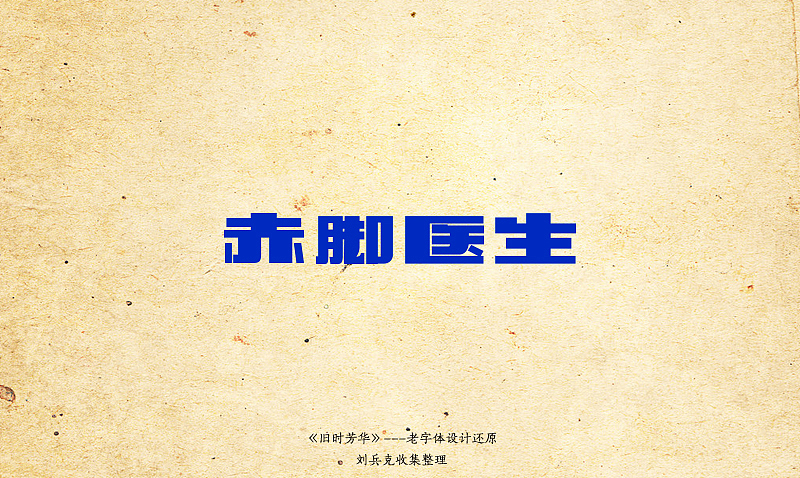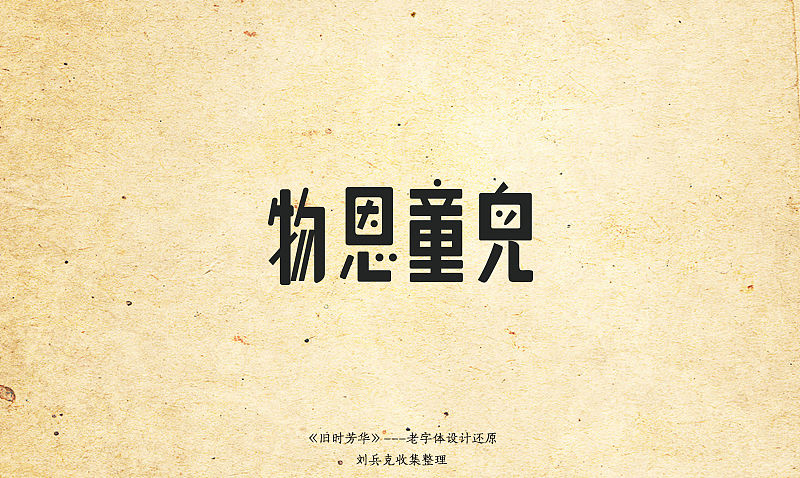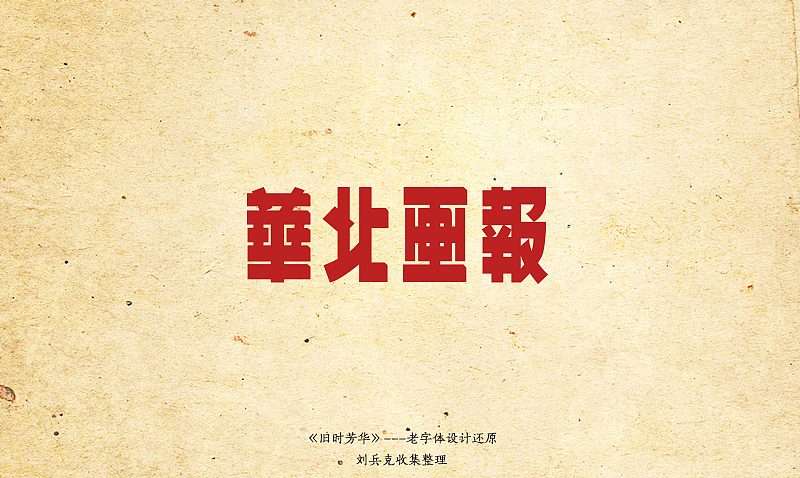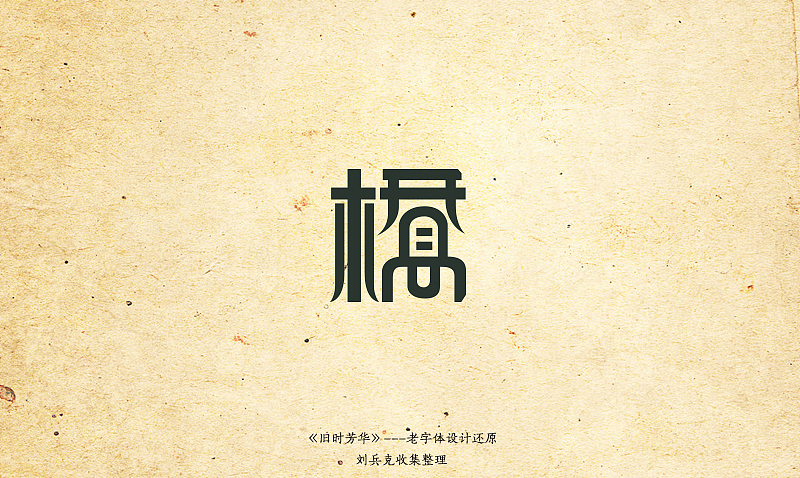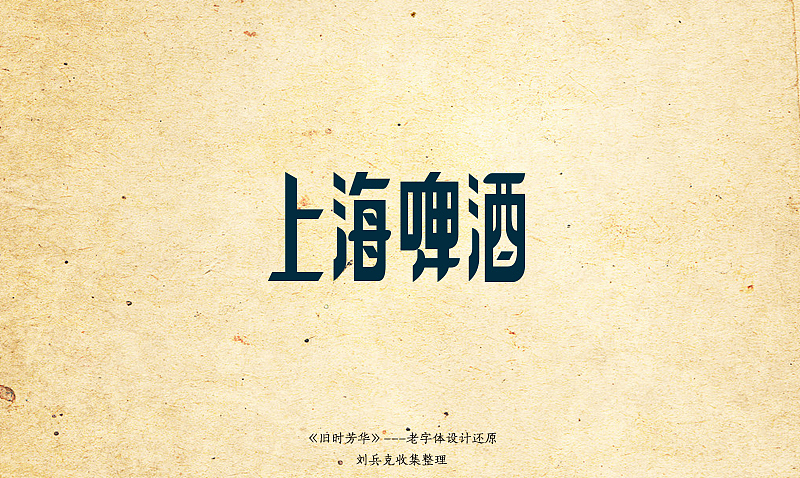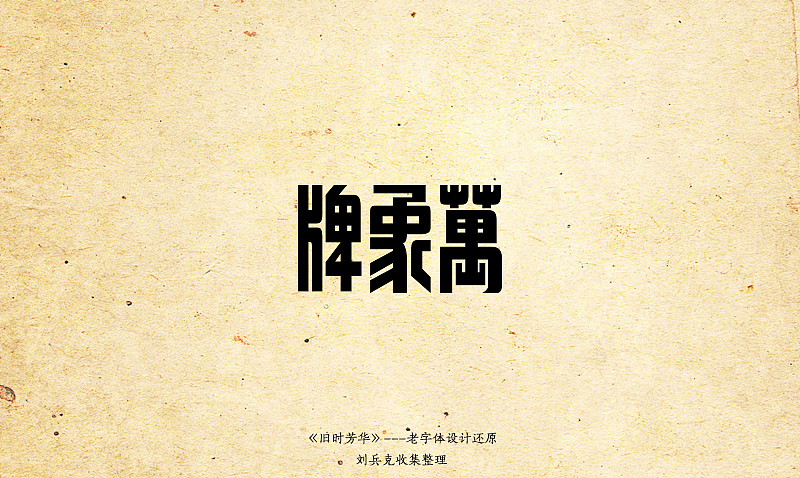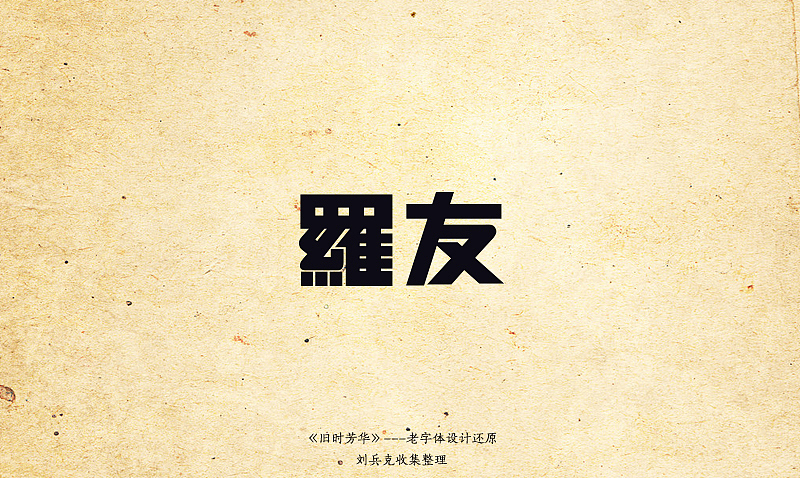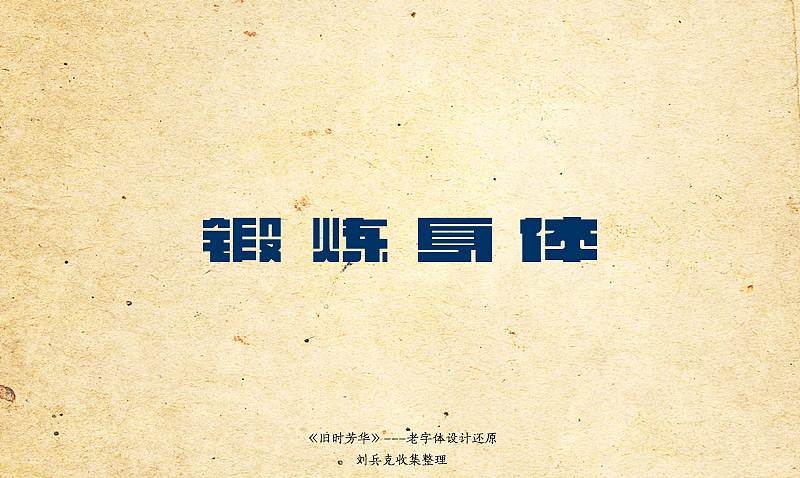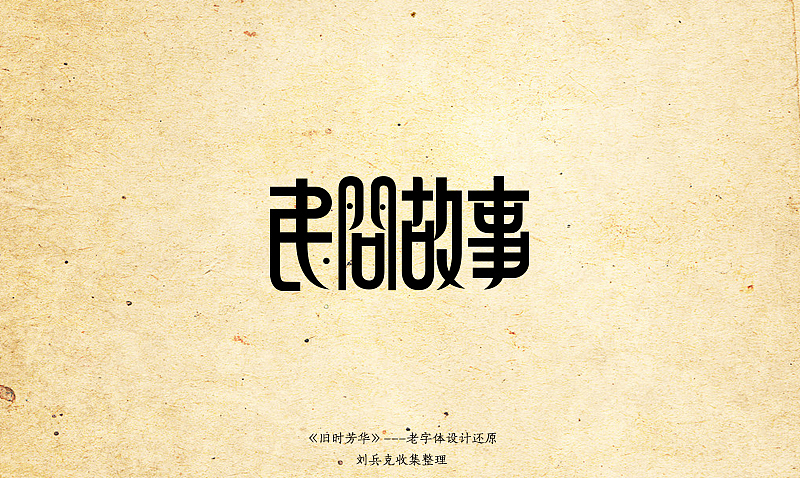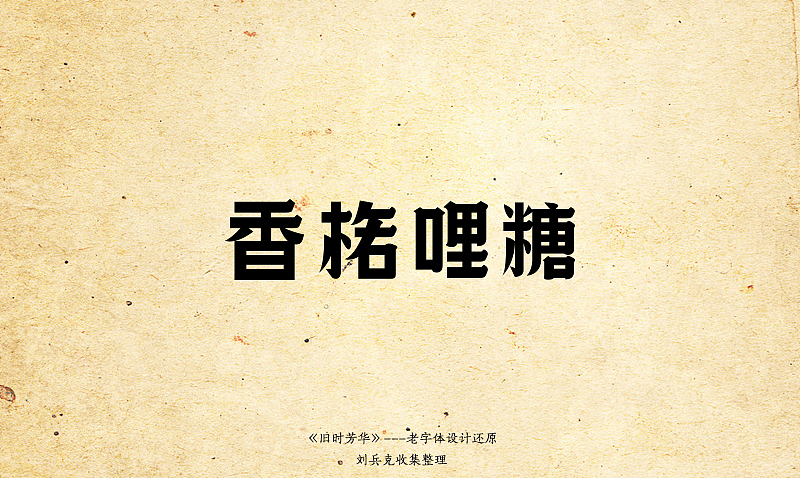
《旧时芳华》---老字体设计还原(C,74-106)
有朋友说这样的老字体在设计细节上有很多的问题,并不是很耐看……
我想说的是:我们更应该看重好的一面,这些字体中,存在着当今设计中所缺失的某些元素,也许我们只发现了其中的一点,或者只是某个字体给了你新的灵感,这就足够了,只要你用心观察,能够灵活转化和运用,便可以让我们受益良多……